Para entender como um estúdio de design como o 2K/Denmark cria o que muitos consideram alguns dos livros mais bonitos do mundo, é preciso observar atentamente a mecânica do invisível da leitura.
Para grande parte dos leitores, por mais que o ditado solicite para que isso não seja feito, um livro é julgado por sua capa ou por suas ilustrações. Porém, para o designer dinamarquês Klaus Krogh e sua equipe na 2K/Denmark, a verdadeira importância do design de livros reside no espaço que não se vê. Quando seu estúdio recebeu a tarefa de tipografia e o layout da segunda edição da Liturgia das Horas da Ascension, Klaus Krogh não estava apenas organizando texto em uma grade. Ele buscava a construção de um objeto físico destinado a ser aberto diariamente, ao longo do próximo meio século.
No vídeo que me apresentou todo esse projeto e o trabalho por trás desse livro, Klaus Krogh parece rejeitar a ideia de que lemos soletrando palavras letra por letra. Em vez disso, nossos cérebros percebem as palavras de forma instantânea como formas geométricas completas. Esse fenômeno é o que Klaus Krogh chama de letterscapes, algo que pode ser traduzido livremente como paisagens de letras. Segundo o designer, quando um leitor abre uma página de um livro, ele reconhece essas estruturas como se estivesse lendo ideogramas ou logos.
Não sei se enxergo as coisas da mesma forma que Klaus Krogh, mas aprecio bastante seu conceito. E ele diz isso porque acredita que a composição tipográfica exige um nível de detalhamento quase microscópico. O design teoriza que, por mais que o desenho de um caráter represente apenas 5% da carga de trabalho de um designer de tipografia, os outros 95% são dedicados às relações espaciais. Afinal, o espaçamento de cada dupla de letras deve ser ajustado individualmente.
Para a Liturgia das Horas da Ascensão, Klaus Krogh e seu 2K/Denmark chegaram a desenvolver uma família tipográfica personalizada: a Ascension Serif. E o designer chega a comparar a tipografia que criou com a fala humana no vídeo que você pode ver aqui nesse artigo. Sua ideia é que a Ascension Serif atue como um tom de voz dessas orações históricas.
Algo que eu achei interessante no ponto de vista do designer é como seu projeto não foi feito para ser usado agora. Seu objetivo é um ciclo de vida litúrgico de 50 anos. Dessa forma, as páginas dessa edição do livro precisam ser conferidas inúmeras vezes pelos designers e editores. Cada quebra de linha e suas margens precisam ser minuciosamente analisadas para eliminar qualquer atrito visual.
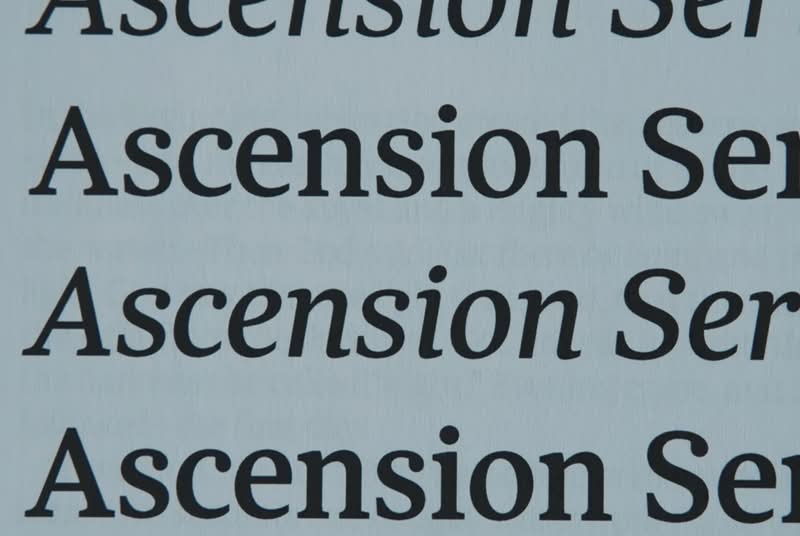
Klaus Krogh acredita que a beleza estrutural do livro influencia diretamente a capacidade do coração humano de se conectar com um texto. Ao tratar as palavras com um cuidado extremo, a geometria final da página deixa de ser um bloco denso de tinta, tendo sido vista como uma porta aberta para um novo mundo.
Esse é o objetivo de Klaus Krogh, ele quer fazer com que os leitores se sintam imediatamente acolhidos sempre que abrirem o livro. E é por isso e outras coisas que o 2K/Denmark é conhecido por fazer os livros mais bonitos do mundo.